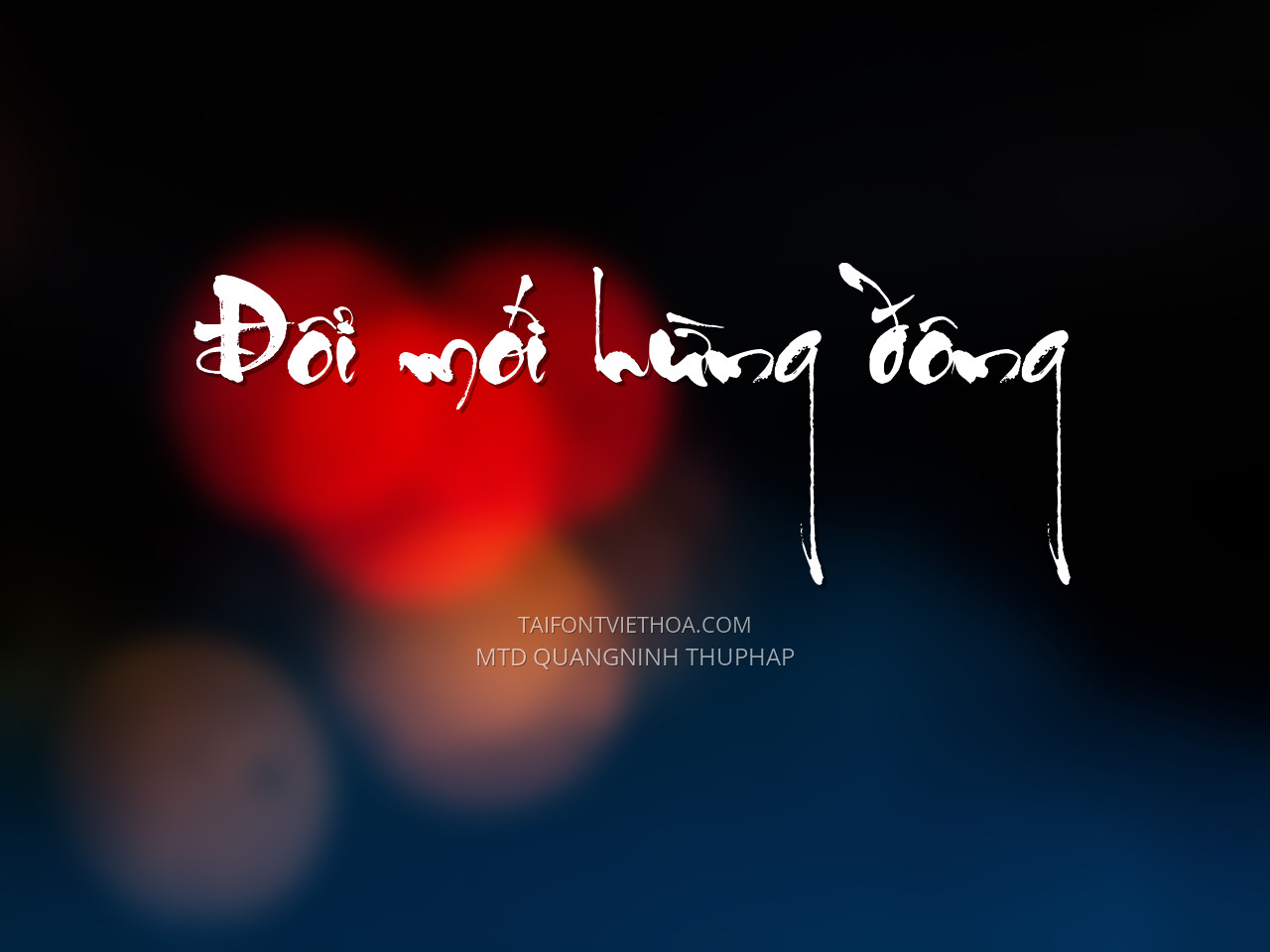
Giới thiệu về font Thư Pháp Quang Ninh
Thư Pháp Quang Ninh là một bộ font thư pháp Việt độc quyền, mô phỏng nét bút lông truyền thống mang đậm tinh thần văn hóa Á Đông. Bộ font được sáng tạo và phát triển bởi các tác giả trong nước nhằm tái hiện lại vẻ đẹp cổ kính, mềm mại và uyển chuyển của chữ viết thư pháp Việt, thường xuất hiện trên câu đối, hoành phi hoặc thư họa truyền thống. Bộ font đã được Việt hóa trọn bộ và tối ưu để hiển thị đầy đủ dấu tiếng Việt theo đúng chuẩn Unicode, đồng thời vẫn giữ được phong cách thư pháp thuần Việt rõ nét.
Đặc điểm thiết kế và ứng dụng của font Thư Pháp Quang Ninh
Bộ font sở hữu cấu trúc chữ mềm mại với các nét vẩy mạnh, độ loe đầu bút tự nhiên như được viết bằng cọ thư pháp thực thụ. Mỗi chữ mang đậm dấu ấn cá nhân và cảm xúc, thể hiện sự uyển chuyển, linh hoạt trong từng nét kéo. Bộ font gồm nhiều biến thể để người dùng lựa chọn cho các kiểu trình bày khác nhau: từ trang trọng, truyền thống đến phóng khoáng, nghệ thuật.
Font Thư Pháp Quang Ninh rất phù hợp cho các dự án thiết kế ấn phẩm Tết, bao lì xì, câu đối thư pháp, backdrop sân khấu, pano văn hóa, tem nhãn sản phẩm truyền thống, và cả trong lĩnh vực sáng tạo liên quan đến nghệ thuật dân gian. Các ngành nghề như: quảng cáo mùa Tết, thiết kế văn hóa, in ấn truyền thống, mỹ thuật thư pháp số sẽ tận dụng rất tốt bộ font này.